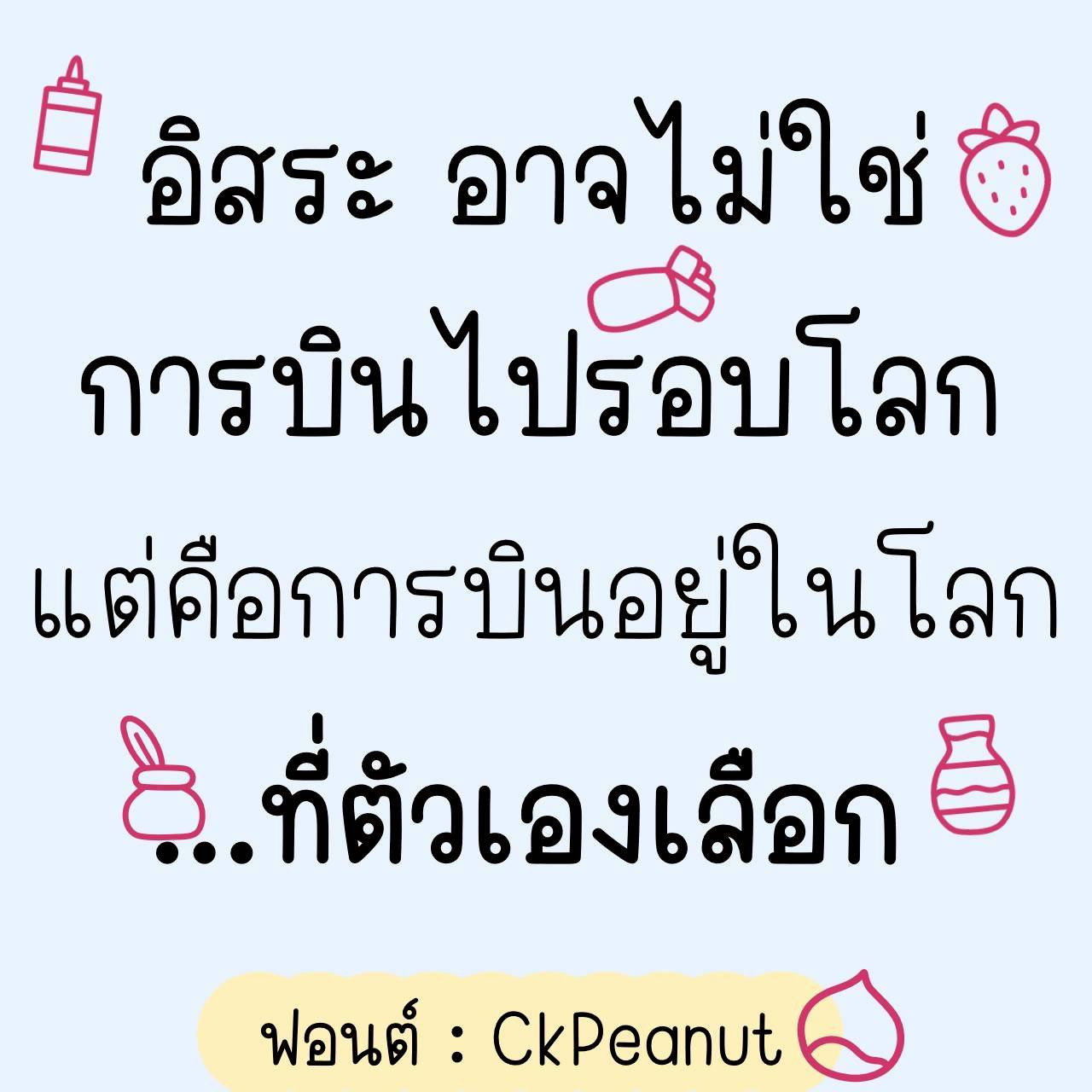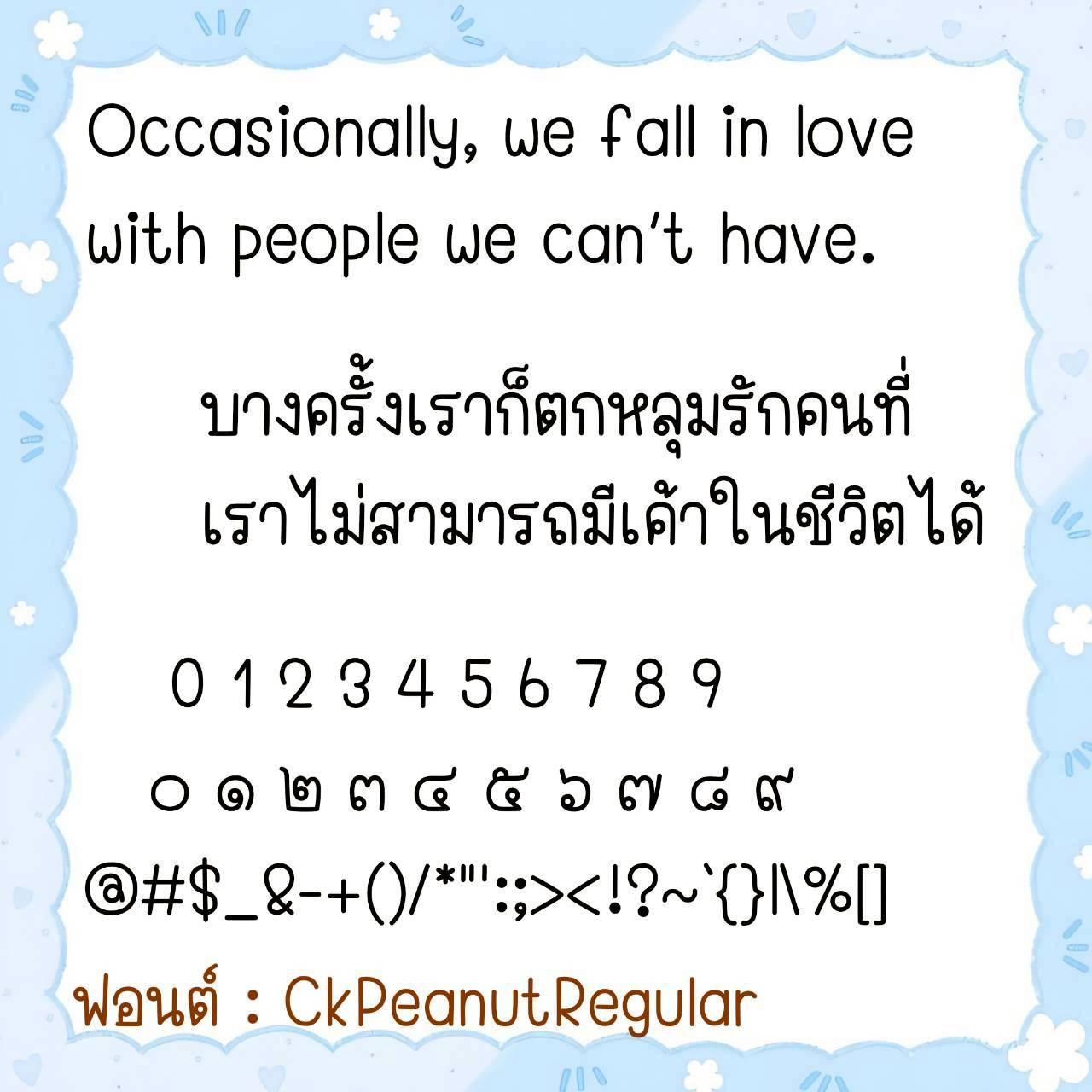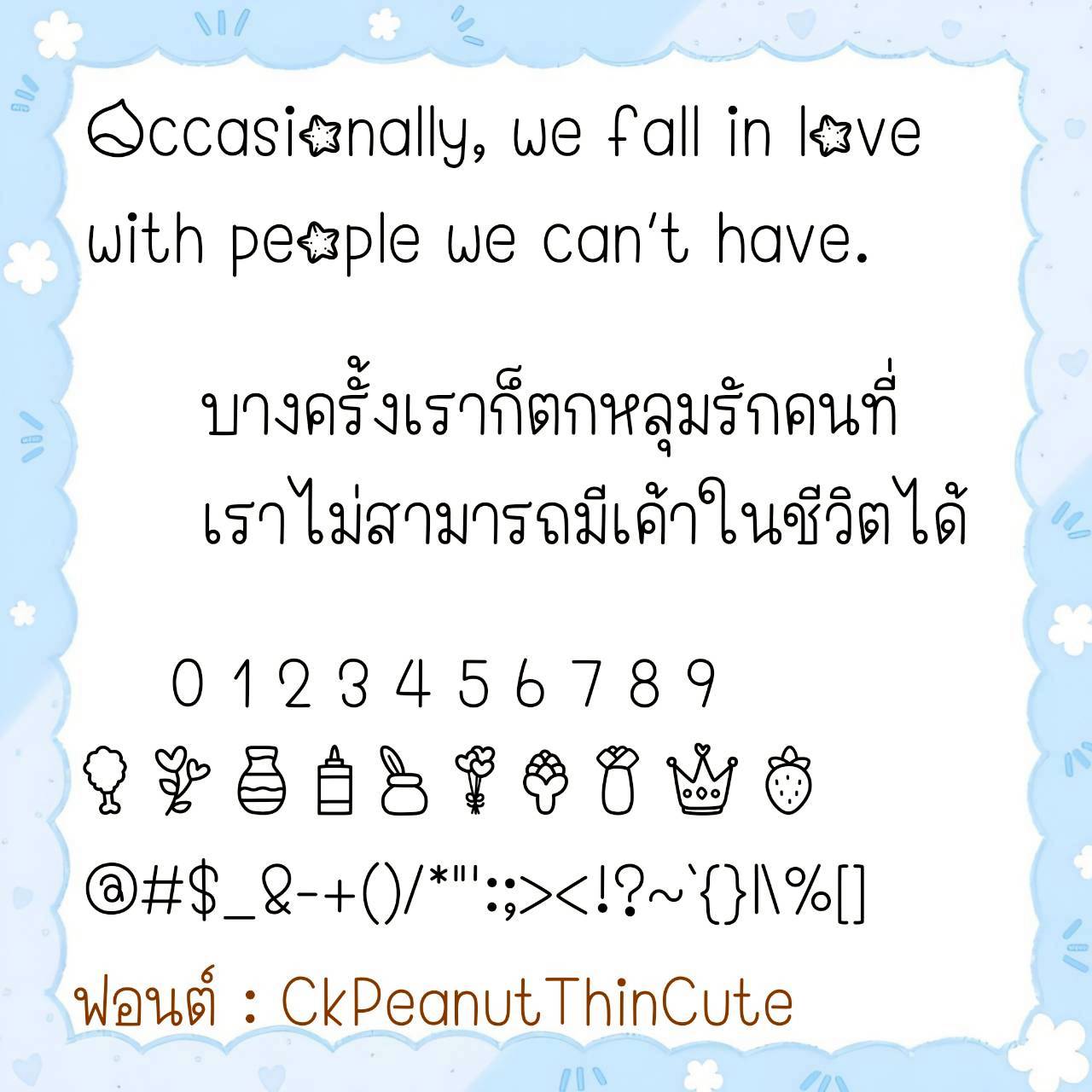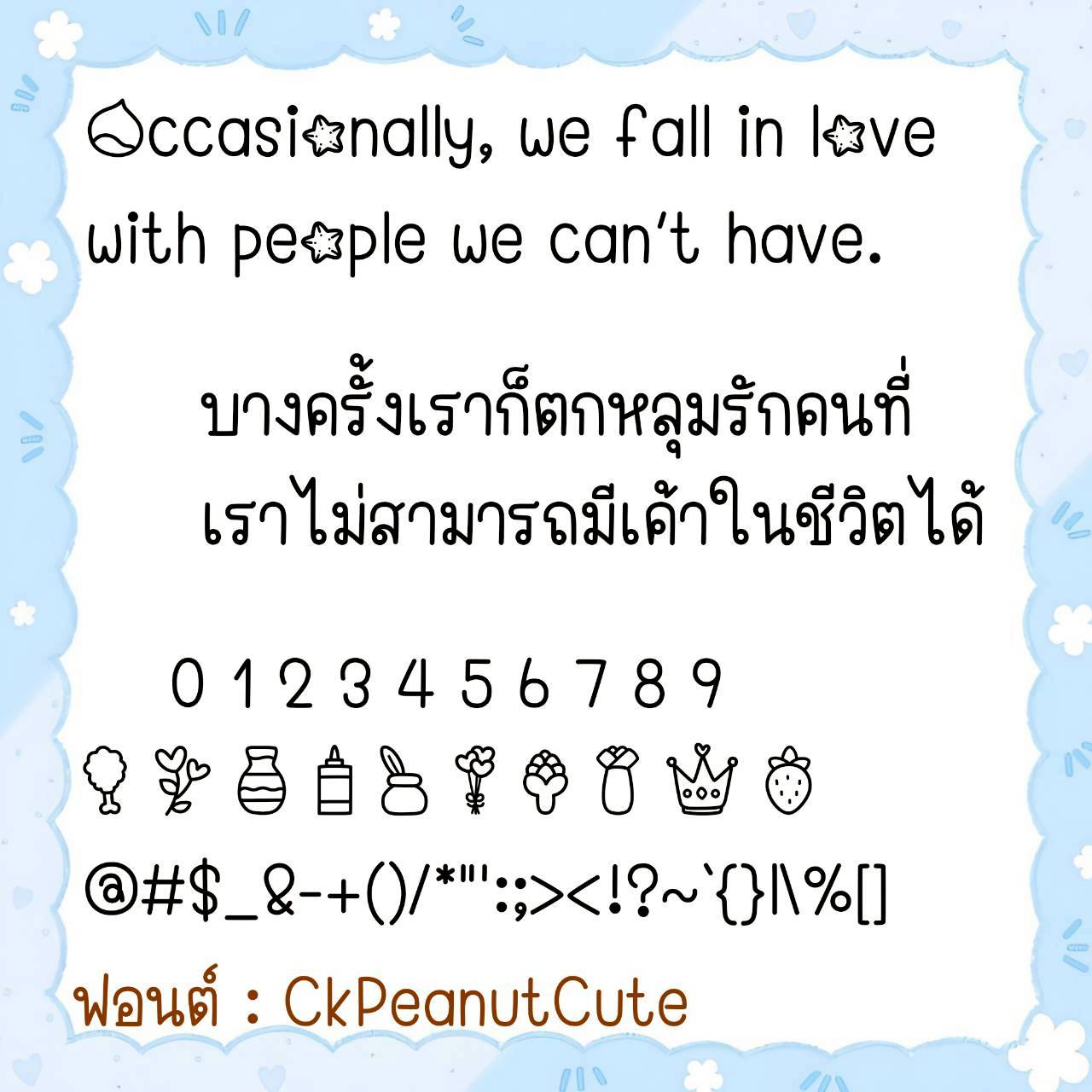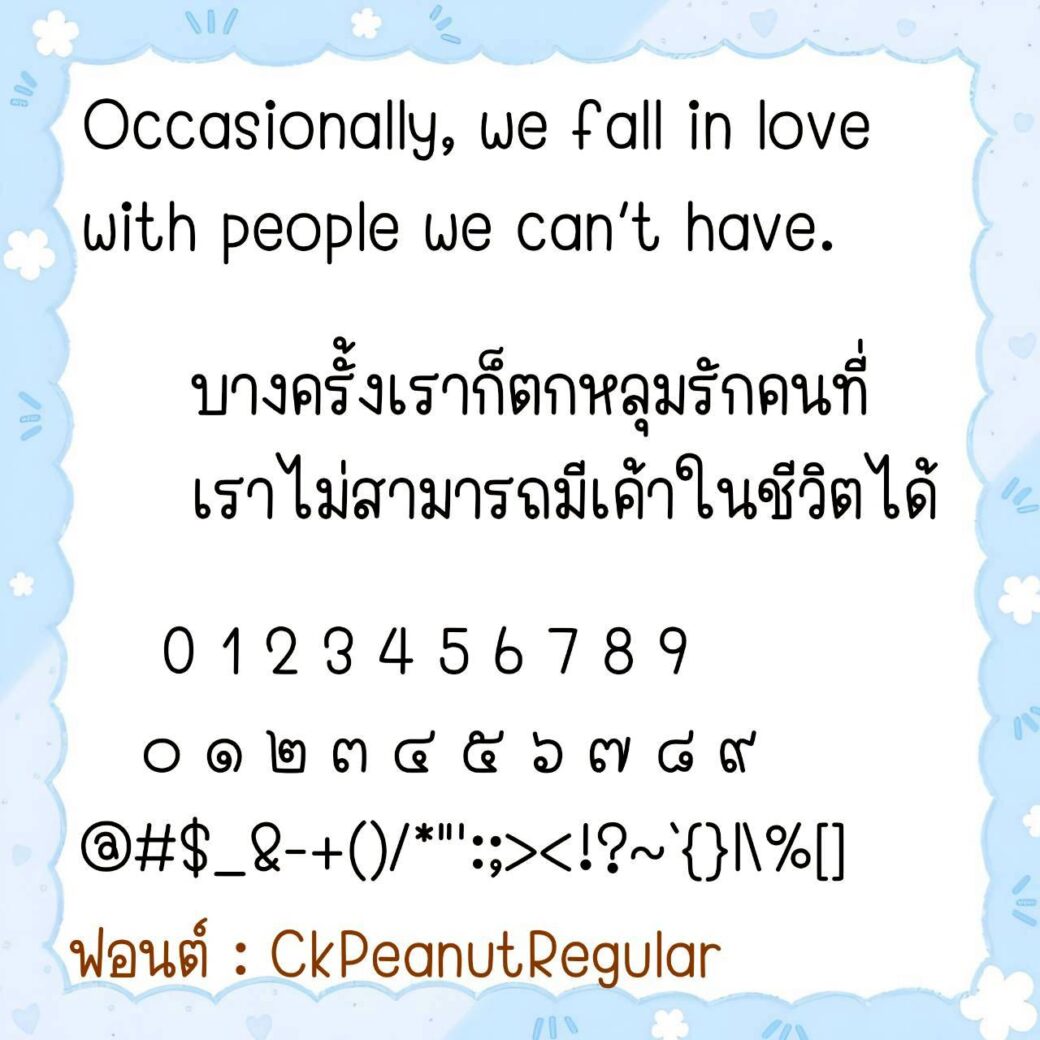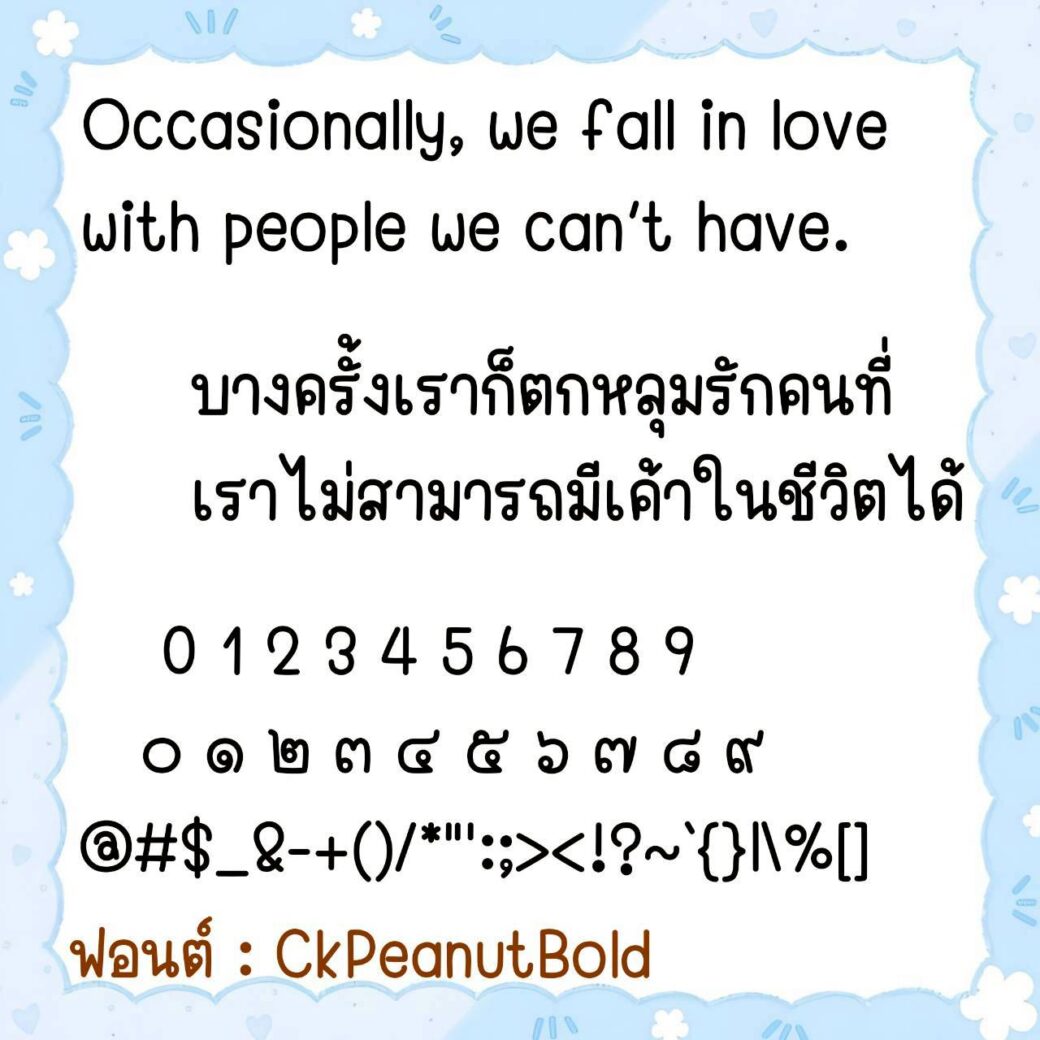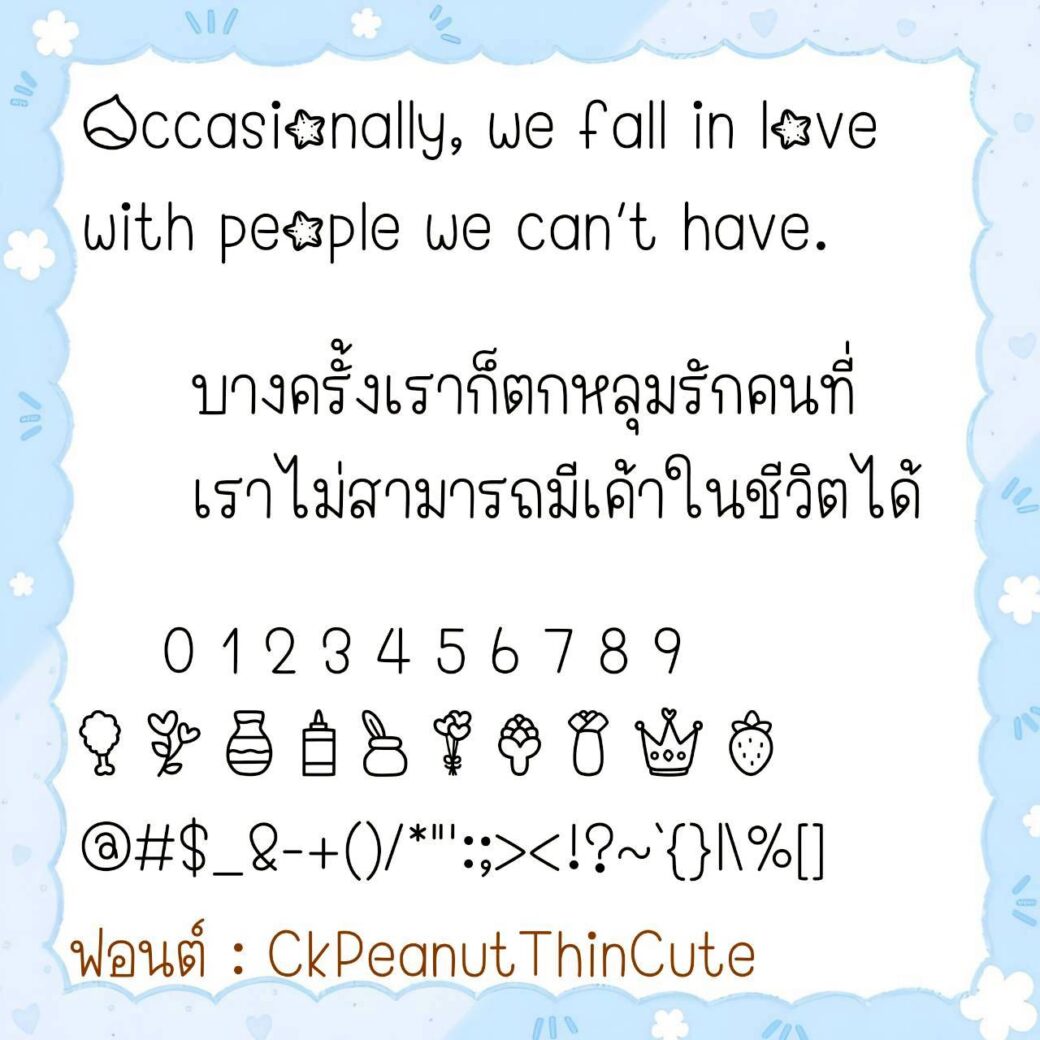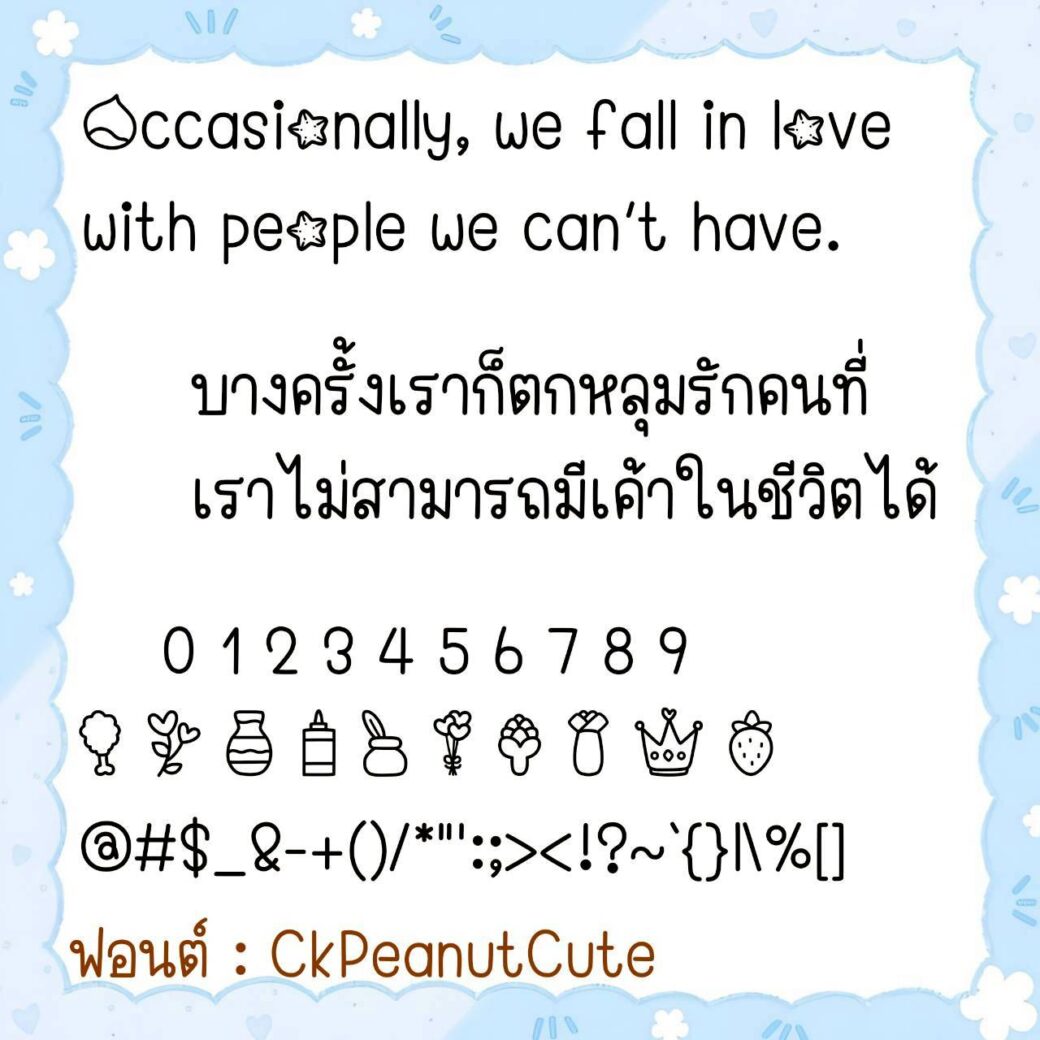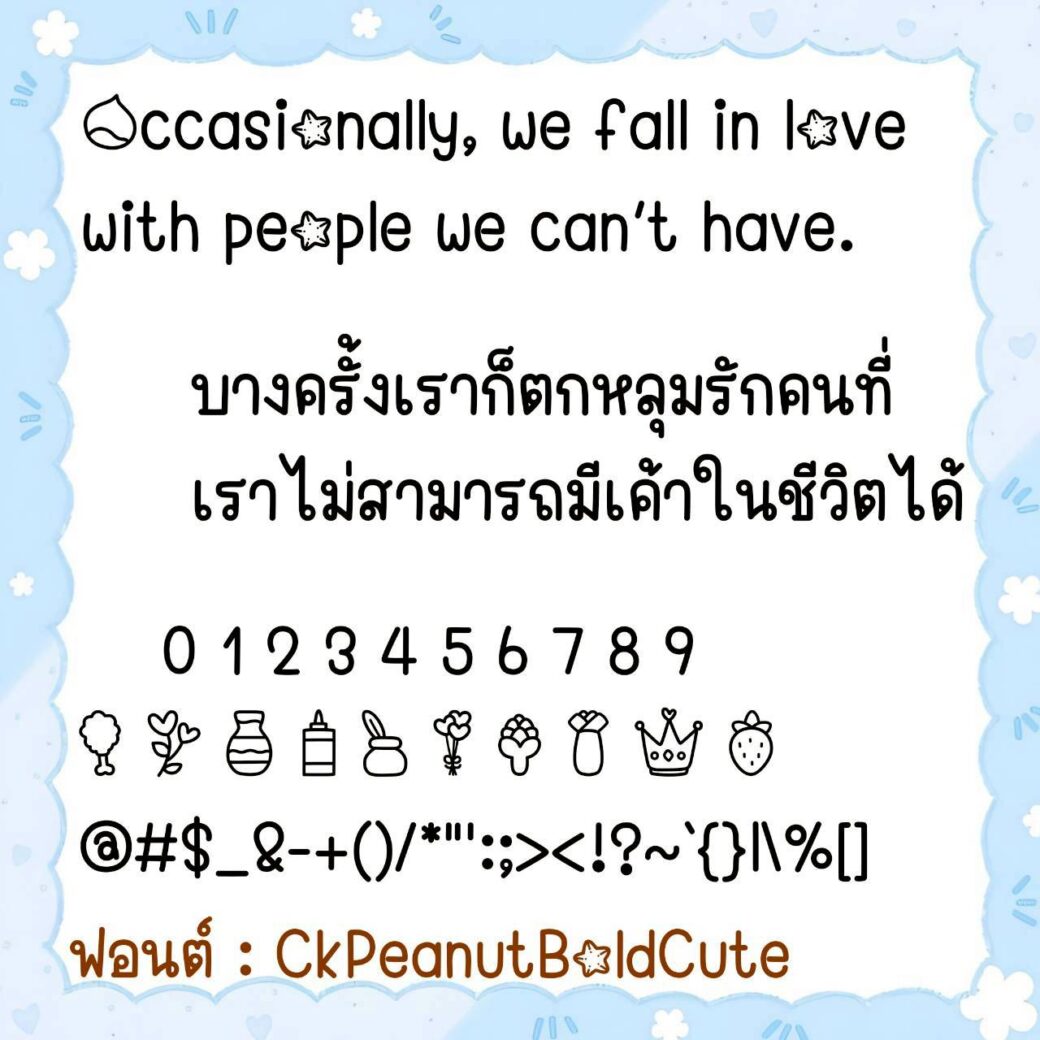
Font CkPeanut
ชื่อสินค้า : Font CkPeanut 💙
🔸 ฟอนต์ลายมือแนวกึ่งเป็นระเบียบ แต่ยังดูมีลูกเล่นเพื่อให้ฟอนต์ดูน่ารักผสมอยู่ในตัว เน้นอ่านง่ายสบายตา และยังมีไฟล์อิโมจิน่ารักๆ ที่ใช้แทนเลขไทยให้ด้วยค่ะ 🥰💙
🔹 A semi-regular handwriting font, but still has a playful touch to make the font look cute. It emphasizes easy reading and is easy on the eyes. There is also a cute emoji file that can be used instead of Thai numerals. 🥰💙